Divis
Das Divis ist ein Interpunktionszeichen; orthographisches Satzzeichen; typografischer Terminus für einen kurzen waagerechten Strich. Auch als »Bindestrich«, »Trennstrich« oder »Viertelgeviertstrich« bezeichnet.
Das Divis teilt Wörter am Zeilenende 1) und verknüpft zusammengehörende Teilbegriffe, Werte und Zahlen (siehe auch Zahlengliederung). Es ist nicht mit dem längeren Halbgeviertstrich (Gedankenstrich) 2) 3) oder dem Minuszeichen (Subtraktionszeichen) zu verwechseln.
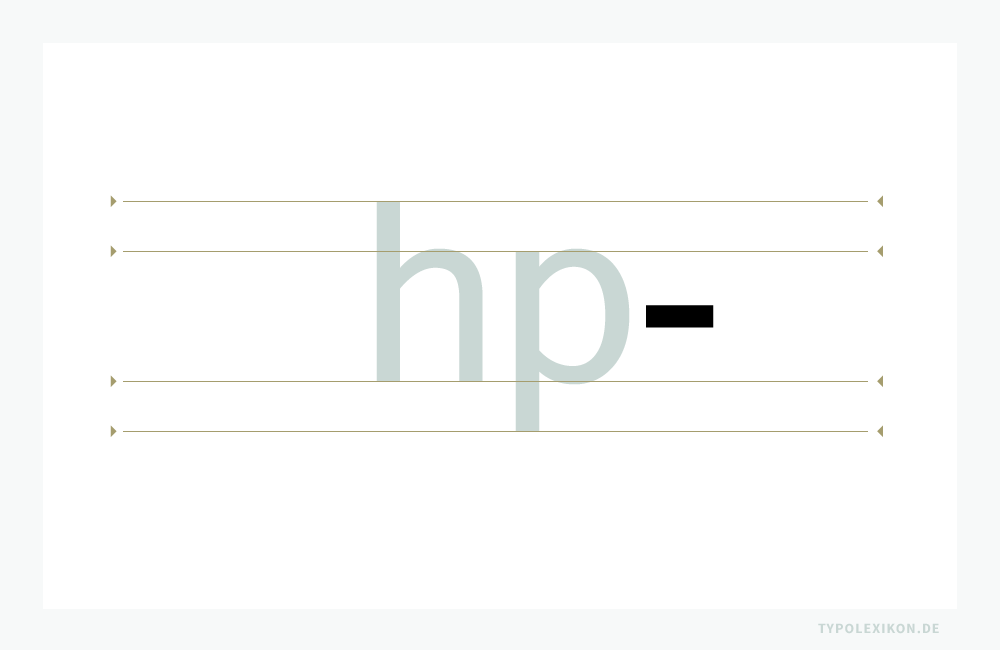
Das Divis ist über eine PC-Standardtastatur, z.B. nach DIN 2137-T2, mit einer Taste eintippbar. Für die Zeichencodierung existieren unterschiedliche ISO-Normen. 4)
| ↑1 | Tipp: Im Blocksatz oder bei einem rechtsbündigen Flattersatz sollte das Divis bzw. ein Teil davon im Sinne des Optischen Randausgleichs über die rechte Satzkante gestellt werden. |
| ↑2 | Anmerkung: Bei »von (…) bis (…)« in Datum- oder Uhrzeitangaben wird kein Divis benutzt, sondern ein Gedankenstrich ohne Leerraumzeichen (z.B. 2001–2007 oder 16:00–17:30 Uhr). |
| ↑3 | Anmerkung: Telefonnebenstellen werden durch einen Divis getrennt (z.B. Telefon 030.2887589-0). |